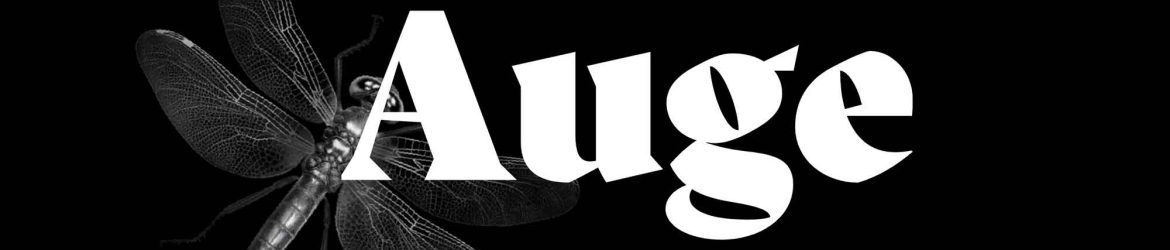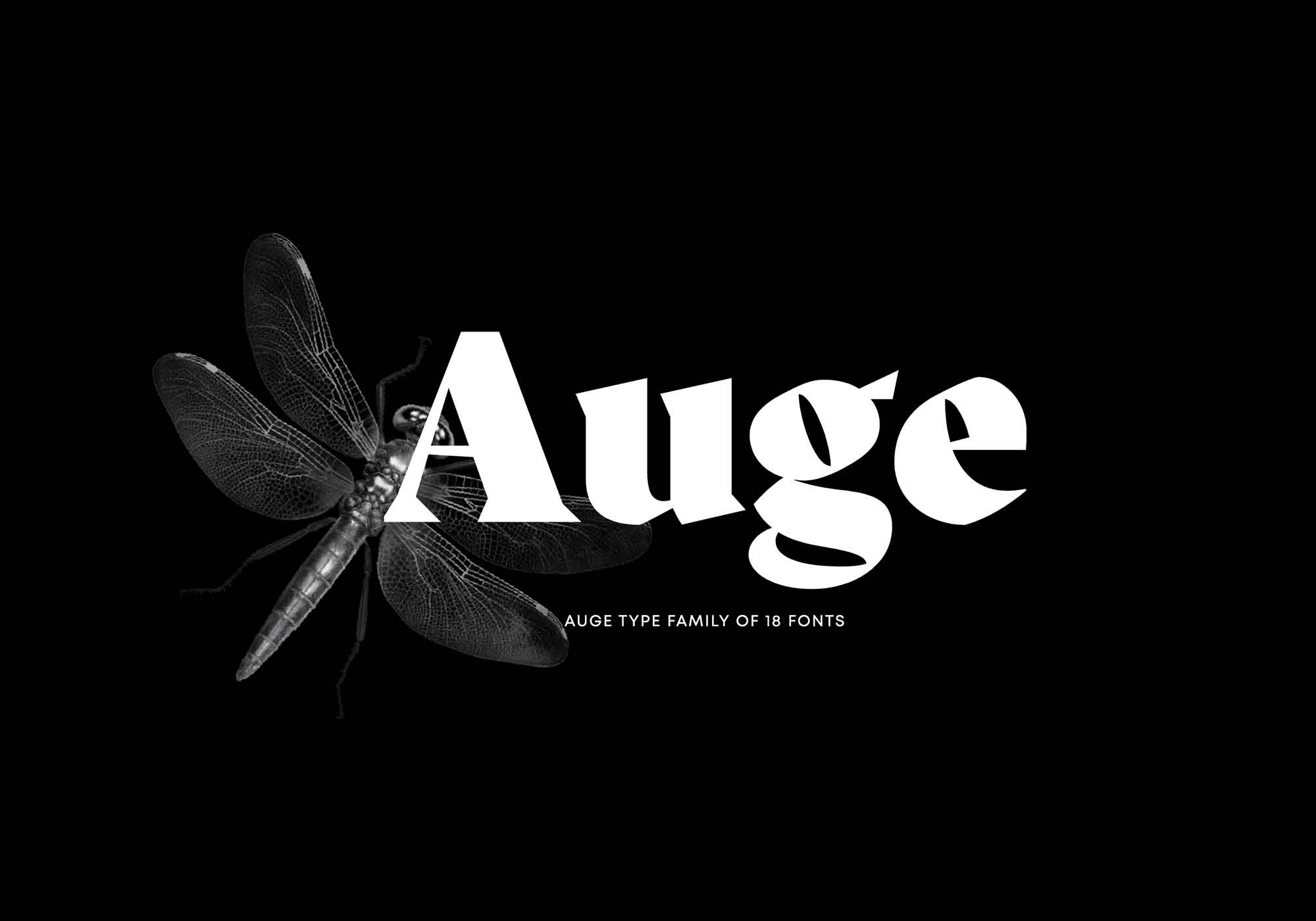
Auge Font Family
Auge é uma família de fontes serifadas, inspirada nos pequenos insetos e no micro-mundo. Sua forma retangular é atraente e versátil, capaz de trazer um ar alegre e vibrante a qualquer projeto de design. O OpenType vem acompanhado de recursos úteis, como ligaturas comuns, superscritos, ordinais, e muito mais. A fonte vem com letras maiúsculas e minúsculas em latim e cirílico, números, pontuação, símbolos e separadores. Font Fabric apresenta Auge em uma versão grátis ou completa que inclui 18 pesos da família. Esta fonte é perfeita para criar uma identidade visual moderna e interessante, sejam você estilizando uma revista de ciência ou criando uma marca de alimentos. Experimente Auge e adicione um toque de diversão e detalhes à sua próxima criação.